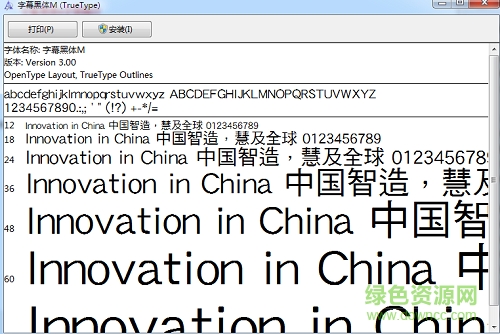
字幕黑體m字體是一款常規(guī)的黑體字體,纖細(xì)的字形但是又有黑體的醒目感,適合用在各種字幕中,感興趣的朋友趕緊來綠色資源網(wǎng)免費(fèi)下載吧!
字幕黑體m是一款常用語字幕的黑體字體,它與黑體結(jié)構(gòu)相同,但點(diǎn)畫粗壯且粗細(xì)一律,起止皆方,氣象豐滿。字體空間的分配,色彩度的感應(yīng)變化及字體視覺真實與假象的運(yùn)用,讓這款字體都與眾不同!